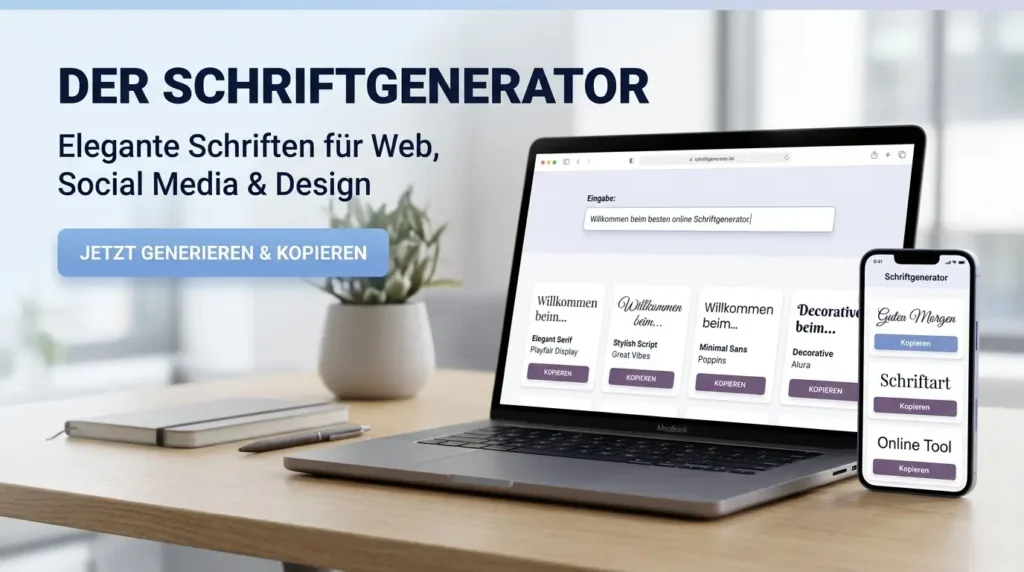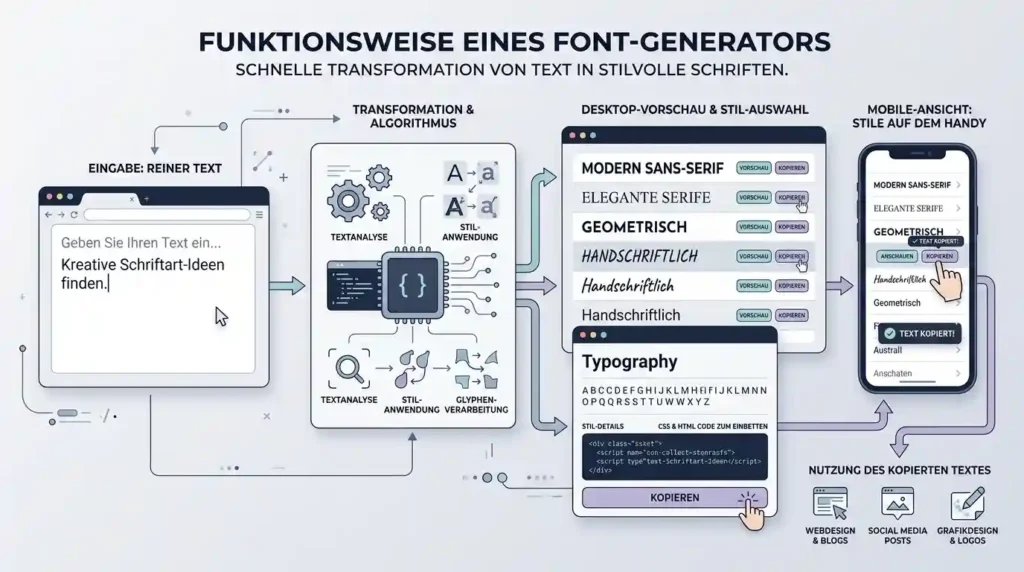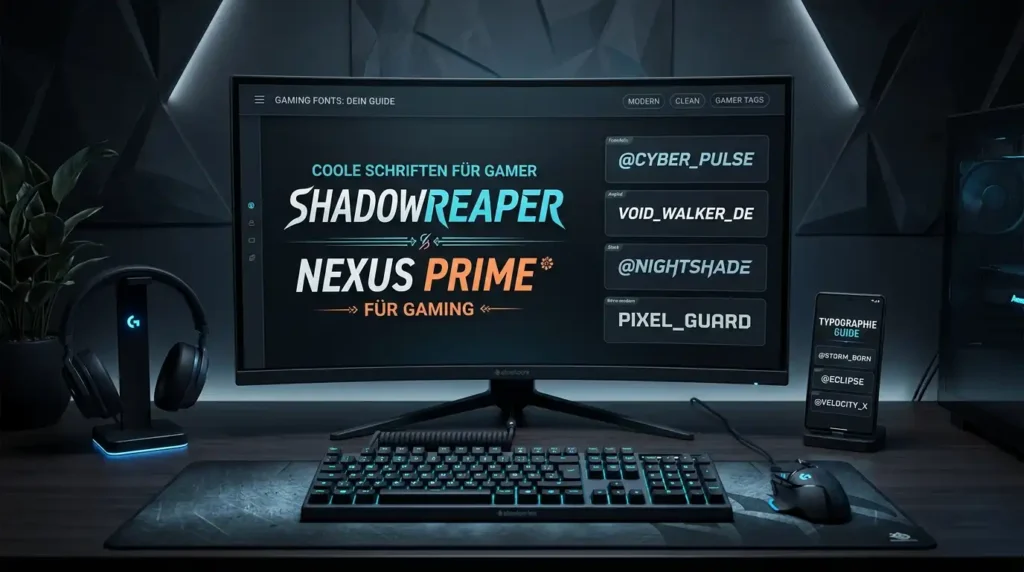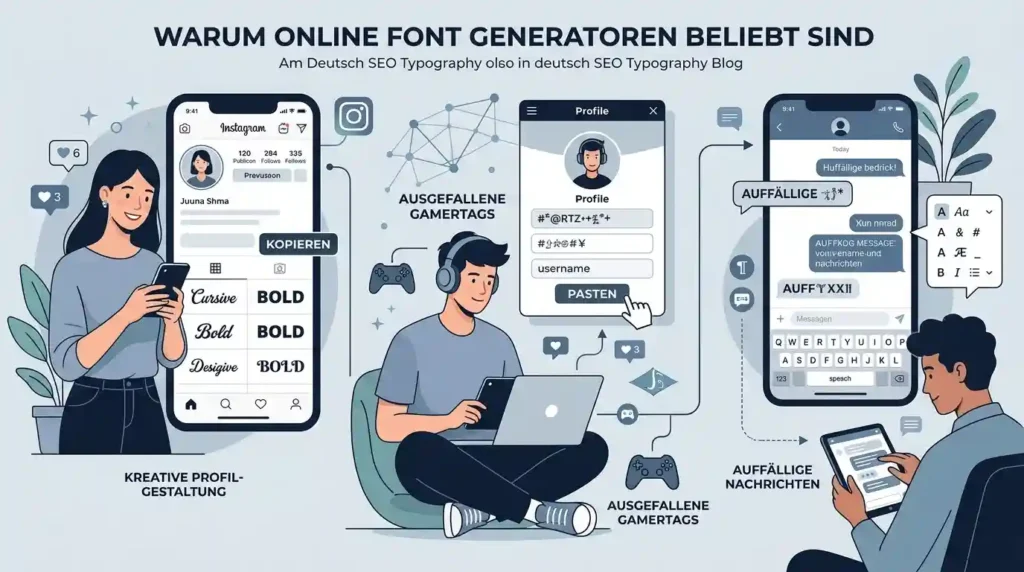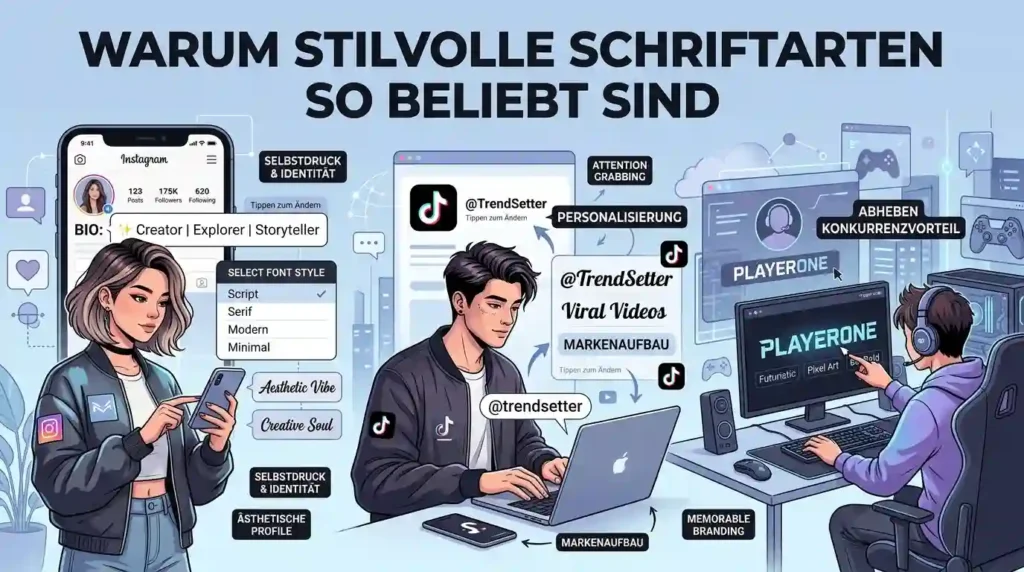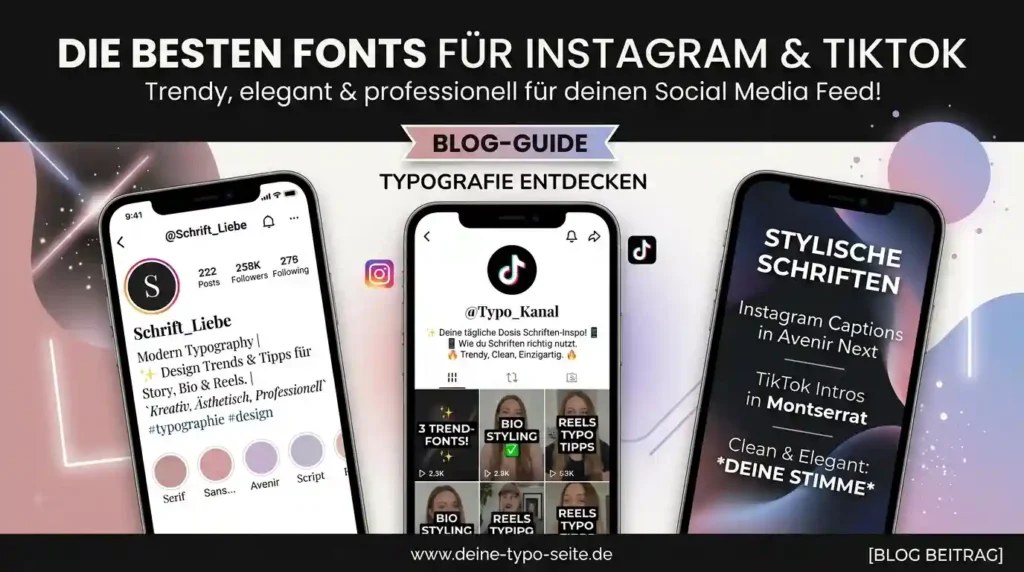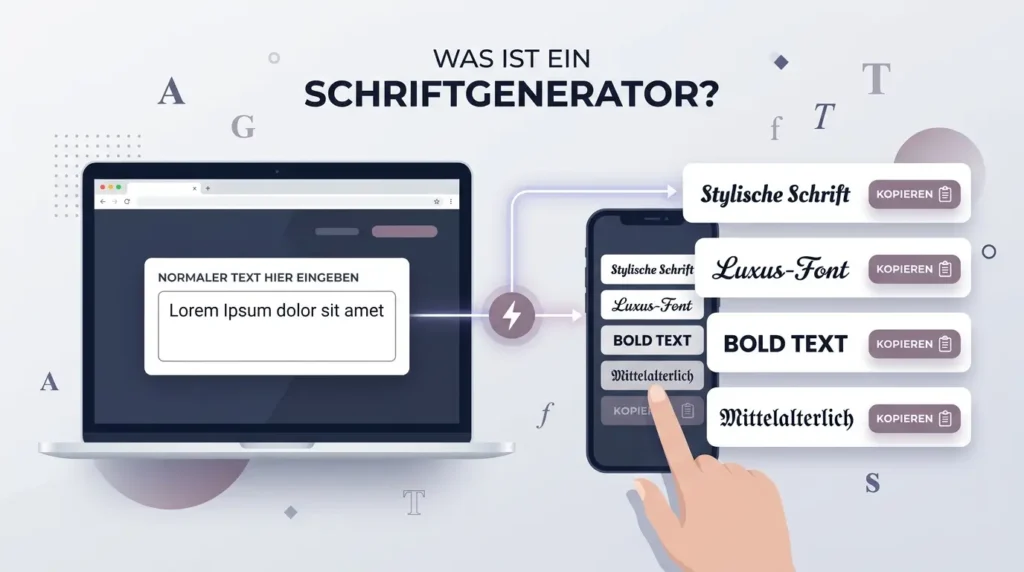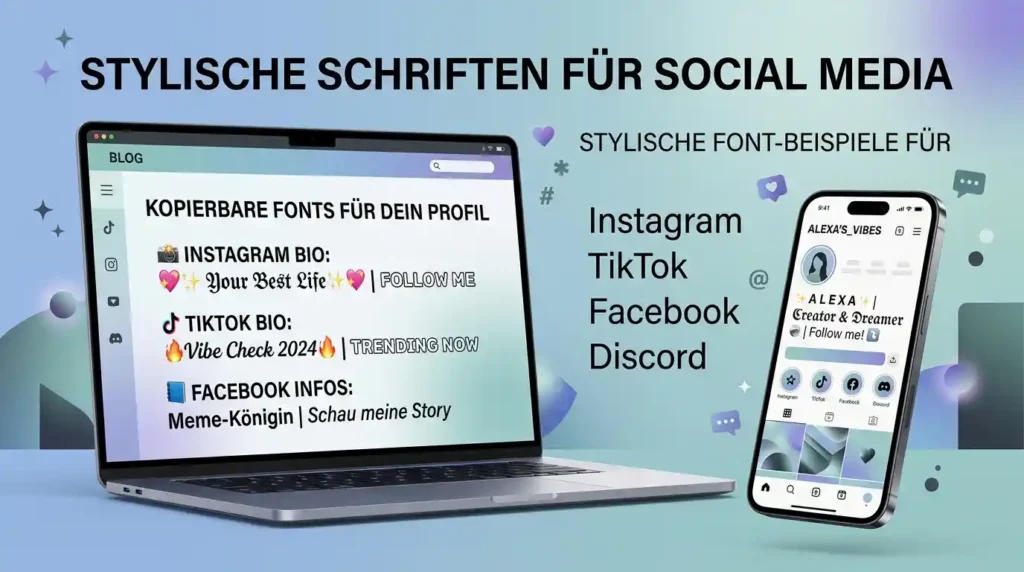
Schriftarten Generator für coole Schriftarten zum Kopieren
Coole Schriftarten sind heute wichtiger denn je. Egal ob auf Instagram, TikTok, Discord oder in Online-Spielen – stylische Texte helfen dabei, mehr Aufmerksamkeit zu bekommen und sich von anderen Nutzern abzuheben. Genau deshalb suchen jeden Tag tausende Menschen in Deutschland nach einem Schriftarten Generator, mit dem sie kreative und moderne Schriftarten zum Kopieren erstellen können.
Mit SchriftGenerator.de kannst du ganz einfach normale Texte in stylische Schriftarten verwandeln. Die Plattform bietet zahlreiche moderne Schriftstile, coole Symbole und dekorative Texte, die perfekt für Social Media, Gaming oder persönliche Profile geeignet sind.
Ob du einen einzigartigen Instagram-Namen, eine kreative TikTok-Bio oder einen stylischen Discord-Text erstellen möchtest – ein professioneller schrift generator macht es besonders einfach. In diesem Artikel erfährst du alles über coole Schriftarten, ihre Vorteile und wie du sie optimal nutzen kannst.
Was ist ein Schriftarten Generator?
Was ist ein Schriftarten Generator mit modernen Schriftarten und stilvollen Texten zum Kopieren
Ein Schriftarten Generator ist ein Online-Tool, das normale Texte in kreative und dekorative Schriftarten umwandelt. Dabei werden spezielle Unicode-Zeichen verwendet, die auf den meisten Plattformen unterstützt werden.
Mit einem modernen schriftgenerator kannst du:
• Stylische Texte erstellen
• Schriftarten zum Kopieren generieren
• Namen dekorieren
• Social-Media-Profile verschönern
• Gaming-Nicknames gestalten
• Coole Symbole hinzufügen
Viele Nutzer verwenden solche Tools täglich, um ihre Texte professioneller und kreativer wirken zu lassen.
Warum sind coole Schriftarten so beliebt?
Warum coole Schriftarten auf Social Media und in Gaming-Profilen so beliebt sind
Die Nutzung von stylischen Schriftarten hat in den letzten Jahren stark zugenommen. Besonders junge Menschen möchten ihre Profile individueller gestalten und mehr Aufmerksamkeit auf Social Media bekommen.
Vorteile von coolen Schriftarten
• Mehr Aufmerksamkeit auf Instagram
• Kreative TikTok-Bios
• Professionelle Gaming-Namen
• Einzigartige Discord-Profile
• Moderne WhatsApp-Status-Texte
• Bessere Wiedererkennung
Ein auffälliger Text bleibt länger im Gedächtnis und wirkt oft professioneller als normale Standardschrift.
Schriftarten zum Kopieren für Social Media
Schriftarten zum Kopieren für Social Media mit modernen und stilvollen Textdesigns für Instagram und TikTok
Viele Nutzer suchen gezielt nach schriftarten zum kopieren, weil sie schnell und einfach verwendet werden können. Statt komplizierte Programme herunterzuladen, reicht heute ein einfacher Online-Generator.
Beliebte Plattformen für stylische Schriftarten
• Instagram
• TikTok
• Facebook
• Discord
• Snapchat
Besonders auf Instagram und TikTok sind kreative Schriftarten extrem beliebt, da sie Profile moderner und einzigartiger wirken lassen.
Die besten Schriftarten für Instagram und TikTok
Die besten Schriftarten für Instagram und TikTok mit modernen und stylischen Textdesigns für Social Media Profile
Instagram und TikTok gehören zu den beliebtesten Plattformen weltweit. Deshalb suchen viele Nutzer nach besonderen Schriftarten, um ihre Bios oder Nutzernamen zu verschönern.
Beliebte Schriftstile
• 𝓒𝓸𝓸𝓵𝓮 𝓢𝓬𝓱𝓻𝓲𝓯𝓽
• 𝔊𝔬𝔱𝔦𝔰𝔠𝔥𝔢 𝔖𝔠𝔥𝔯𝔦𝔣𝔱
• Fullwidth
• 𝐅𝐞𝐭𝐭𝐞 𝐒𝐜𝐡𝐫𝐢𝐟𝐭
• 🅒🅞🅞🅛 🅣🅔🅧🅣
Diese Schriftarten helfen dabei, mehr Aufmerksamkeit zu erzeugen und Inhalte optisch interessanter zu gestalten.
Wie funktioniert ein Schrift Generator?
Wie ein Schrift Generator funktioniert mit modernen Schriftarten und stilvollen Texten zum Kopieren
Ein moderner schrift generator basiert auf Unicode-Zeichen. Statt echte Schriftarten zu installieren, werden spezielle Zeichenkombinationen genutzt, die wie verschiedene Fonts aussehen.
So funktioniert es
1. Text eingeben
2. Automatisch verschiedene Schriftarten generieren
3. Lieblingsstil auswählen
4. Text kopieren
5. Auf Social Media verwenden
Der gesamte Prozess dauert nur wenige Sekunden und funktioniert sowohl auf Smartphones als auch auf Desktop-Geräten.
Vorteile von SchriftGenerator.de
Vorteile von SchriftGenerator.de mit modernen Schriftarten und stilvollen Texten für Social Media und Gaming
SchriftGenerator.de gehört zu den beliebtesten deutschen Webseiten für stylische Schriftarten und dekorative Texte.
Vorteile der Plattform
• Schnelle Texterstellung
• Viele moderne Schriftarten
• Kostenlos nutzbar
• Mobilfreundliches Design
• Einfache Bedienung
• Schriftarten sofort kopierbar
• Unterstützt Social Media und Gaming
Die Webseite ist speziell für Nutzer entwickelt worden, die schnell coole Texte erstellen möchten.
Coole Schriftarten für Gaming
Coole Schriftarten für Gaming mit modernen Gamer-Namen und stylischen Textdesigns für Online-Spiele
Nicht nur Social Media, sondern auch Online-Spiele profitieren von kreativen Schriftarten. Viele Gamer nutzen stylische Namen, um professioneller und einzigartiger zu wirken.
Beliebte Spiele
• Free Fire
• Fortnite
• PUBG
• Call of Duty
• Minecraft
• Roblox
Mit einem schriftarten generator können Spieler einzigartige Nicknames erstellen, die im Spiel sofort auffallen.
Beispiele für Gaming-Schriftarten
• 𝕯𝖆𝖗𝖐𝕶𝖎𝖓𝖌
• ★彡Player彡★
• 𝐋𝐄𝐆𝐄𝐍𝐃
• ꧁༒Gamer༒꧂
• 『PRO』
Gaming-Namen mit stylischen Schriftarten wirken moderner und professioneller.
Warum suchen Menschen nach Schriftarten Generatoren?
Warum Menschen nach Schriftarten Generatoren für Social Media, Gaming und kreative Texte suchen
Die Nachfrage nach einem schriftgenerator wächst jedes Jahr weiter. Menschen möchten kreative Inhalte erstellen und ihre Online-Präsenz verbessern.
Häufige Gründe
• Mehr Aufmerksamkeit bekommen
• Profile personalisieren
• Professioneller wirken
• Kreative Inhalte erstellen
• Trendige Texte nutzen
• Mehr Follower gewinnen
Besonders Influencer und Gamer nutzen täglich kreative Schriftarten.
Tipps für die besten Schriftarten
Tipps für die besten Schriftarten mit modernen und stilvollen Textdesigns für Social Media und kreative Inhalte
Nicht jede Schriftart passt zu jedem Profil. Deshalb solltest du einige wichtige Punkte beachten.
Wichtige Tipps
• Nutze lesbare Schriftarten
• Verwende nicht zu viele Symbole
• Halte Texte übersichtlich
• Wähle moderne Designs
• Nutze Schriftarten passend zur Plattform
Eine gute Schriftart sollte auffällig, aber trotzdem leicht lesbar sein.
Schriftarten und SEO
Schriftarten und SEO mit modernen Textdesigns und optimierter Typografie für Webseiten und Social Media
Viele Website-Betreiber nutzen mittlerweile kreative Texte auch für Branding und Social Media Marketing. Besonders auf Pinterest und Instagram können auffällige Texte die Klickrate erhöhen.
Coole Schriftarten verbessern zwar nicht direkt das Google-Ranking, können aber:
• Mehr Engagement erzeugen
• Nutzer länger halten
• Die Markenwirkung verbessern
• Social Shares erhöhen
Dadurch profitieren Webseiten indirekt von mehr Sichtbarkeit.
FAQ
Was ist ein Schriftarten Generator?
Ein Online-Tool, das normale Texte in stylische Schriftarten umwandelt.
Sind die Schriftarten kostenlos?
Ja, auf SchriftGenerator.de können alle Schriftarten kostenlos genutzt werden.
Funktionieren die Schriftarten auf Instagram?
Ja, die Schriftarten funktionieren auf Instagram, TikTok, Discord und vielen weiteren Plattformen.
Muss ich eine App herunterladen?
Nein, der Generator funktioniert direkt im Browser.
Kann ich die Schriftarten kopieren?
Ja, alle Schriftarten können mit einem Klick kopiert werden.
Funktioniert der Schrift Generator auf Smartphones?
Ja, die Webseite ist vollständig mobiloptimiert.
Fazit
Ein moderner schriftarten generator ist die perfekte Lösung für alle, die kreative und stylische Texte erstellen möchten. Egal ob für Instagram, TikTok, Discord oder Gaming – coole Schriftarten helfen dabei, sich von anderen Nutzern abzuheben und Profile professioneller wirken zu lassen.